サンキューシール30mm 文字とハート marianフォント
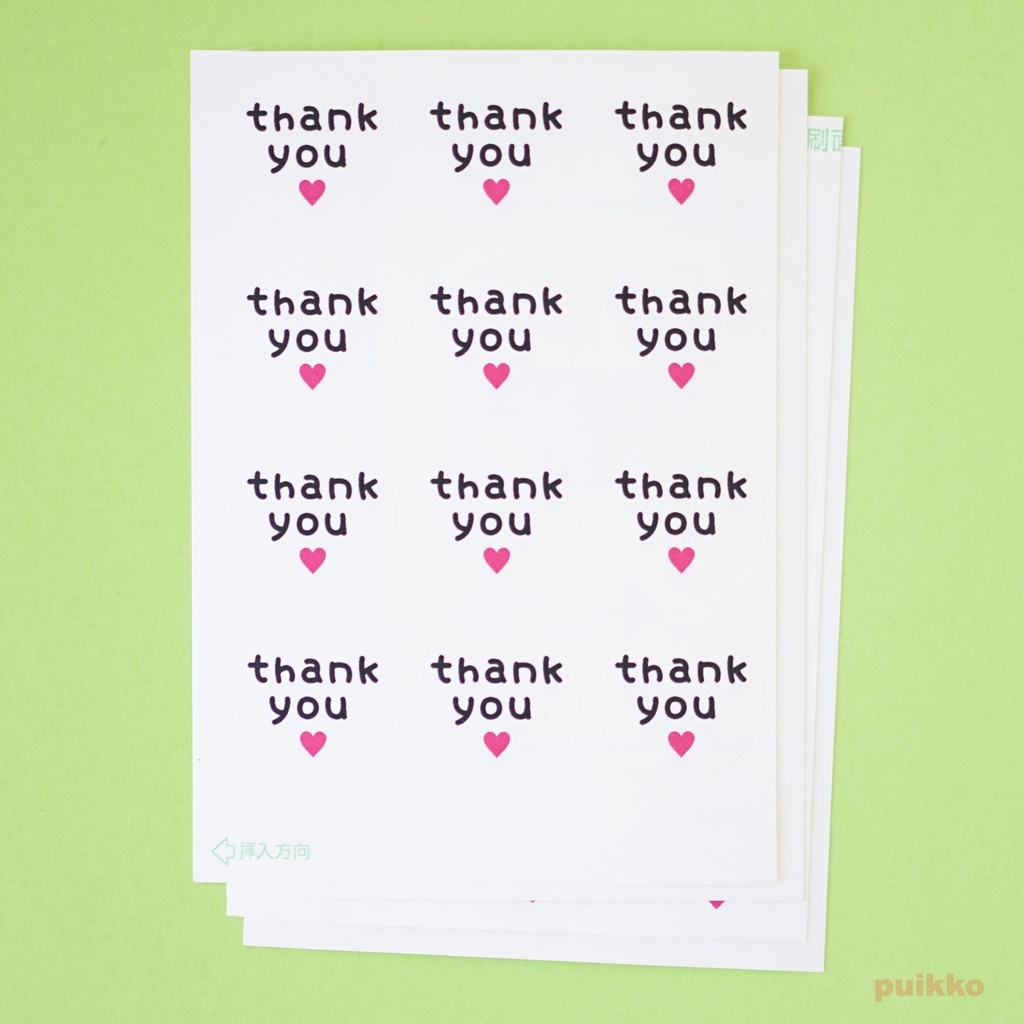
丸型でかわいいフォントのサンキューシールです。 手紙の封かん、ハンドメイド作品の梱包、ちょっとしたプレゼントのラッピングなどにお使いください。 丸型のラベルシールにmarianフォントというpuikkoオリジナルの丸っこいフォントで「Thank you」の文字とハートマーク入り。 ・シールのサイズ 直径30mm ・シールの片数 48片 【素材】 ラベルシール マット紙・ホワイト 【サイズ】 幅210×高さ297mm(A4サイズ) 【購入の際の注意点】 発送する際、シートを4分割します。 市販のインクジェットプリンタを使って印刷しているので、図柄がシールの円の中心からずれていることがあります。あらかじめご了承ください。 防水されていませんので紙濡れにご注意ください。